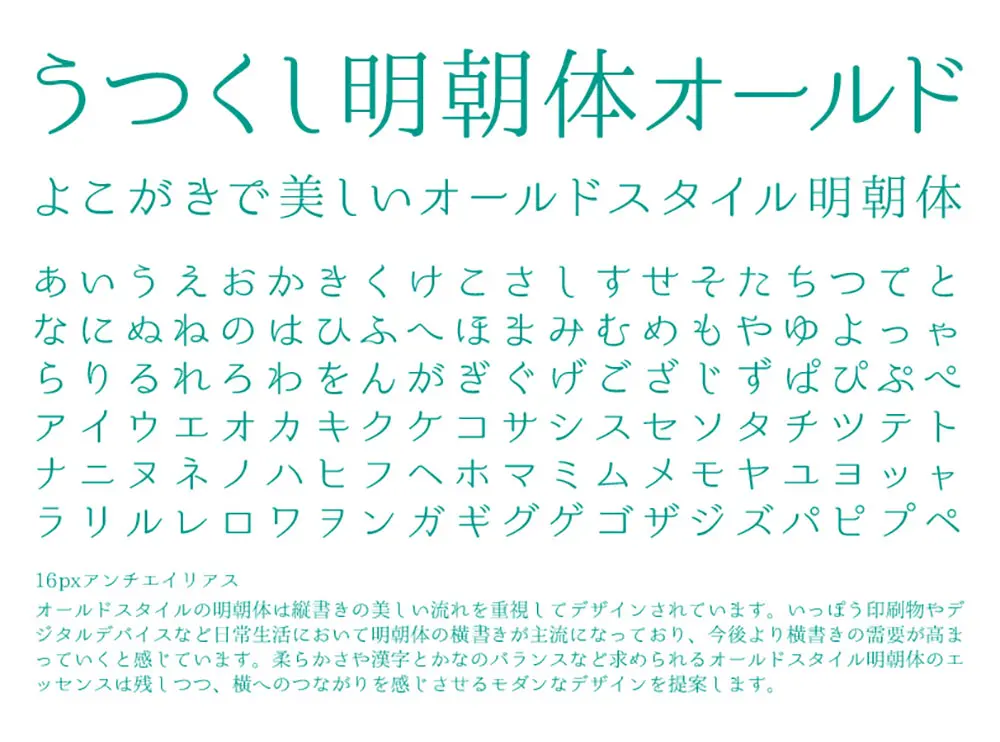
うつくし明朝體基本上是重視豎寫的美麗流程而設計的。在印刷品和數碼設備等日常生活中,明朝體的橫寫成為主流,今後橫寫的需求會更加高漲。“うつくし明朝體+” 在保留古典明朝體的要素,如柔和、復古的風味以及漢字和假名的平衡等的基礎上,採用了更現代的設計,強調與橫排的連接感。垂直和水平的線條都是筆直的,同時也廣泛使用了斜線的直線設計。這是對新概念的古典系列明朝體的設計提案。平假名和片假名贏得了2014年日本印刷年鑑最佳作品獎。
オールドスタイル明朝體は、基本的に縦書きの美しい流れを重視してデザインされています。印刷物やデジタルデバイスなど日常生活において明朝體の橫書きが主流になっており、今後はより橫書きの需要が高まっていくと感じています。うつくし明朝體+は柔らかさ・レトロな味わい・漢字とかなのバランスなど求められるオールドスタイル明朝體のエッセンスは殘しつつ、橫へのつながりを感じさせるモダンなデザインにしました。垂直水平のラインはまっすぐに、また斜めのラインもまっすぐなデザイン多用しました。新しいコンセプトのオールド系明朝體のデザイン提案です。ひらがな・カタカナは日本タイポグラフィ年鑑2014ベストワーク賞。